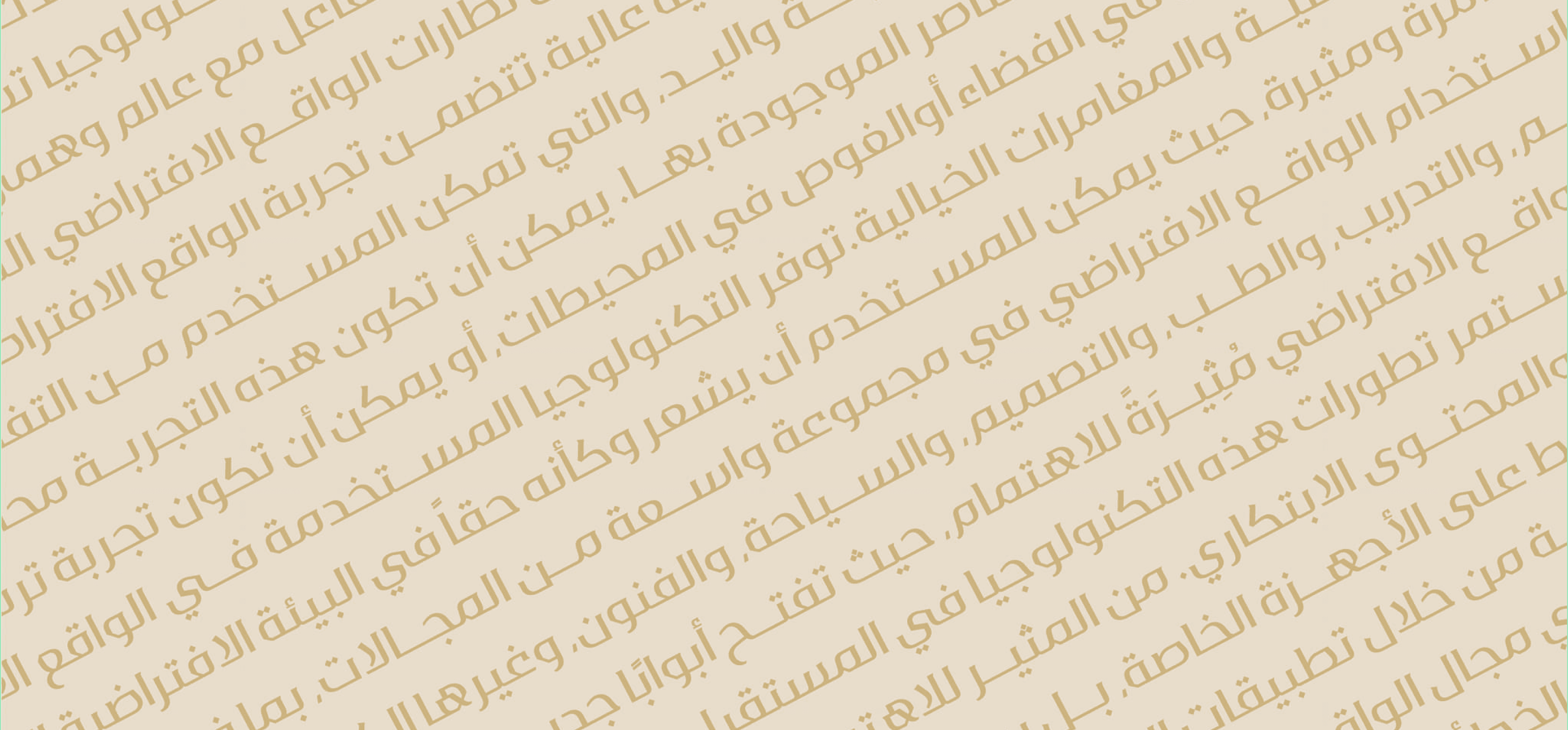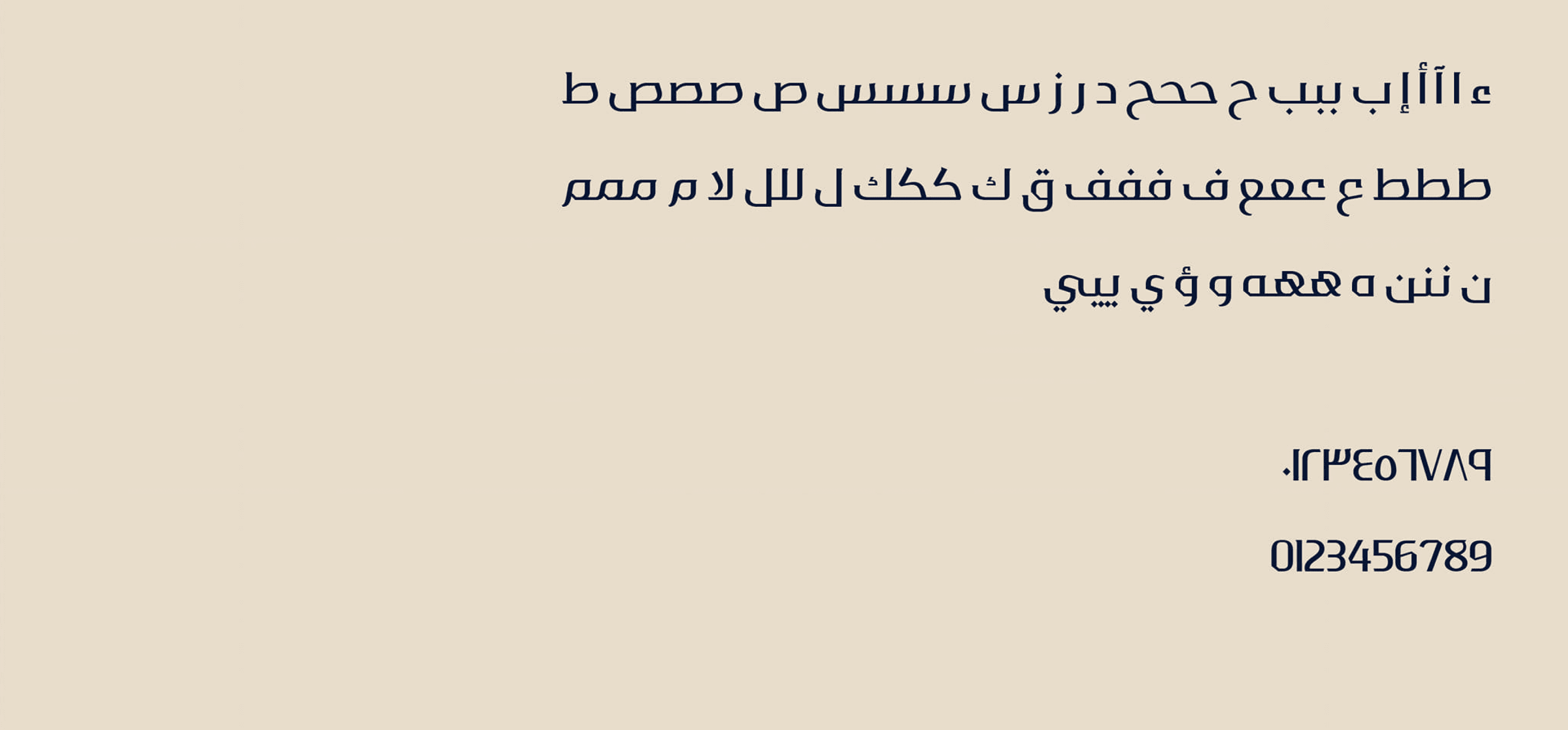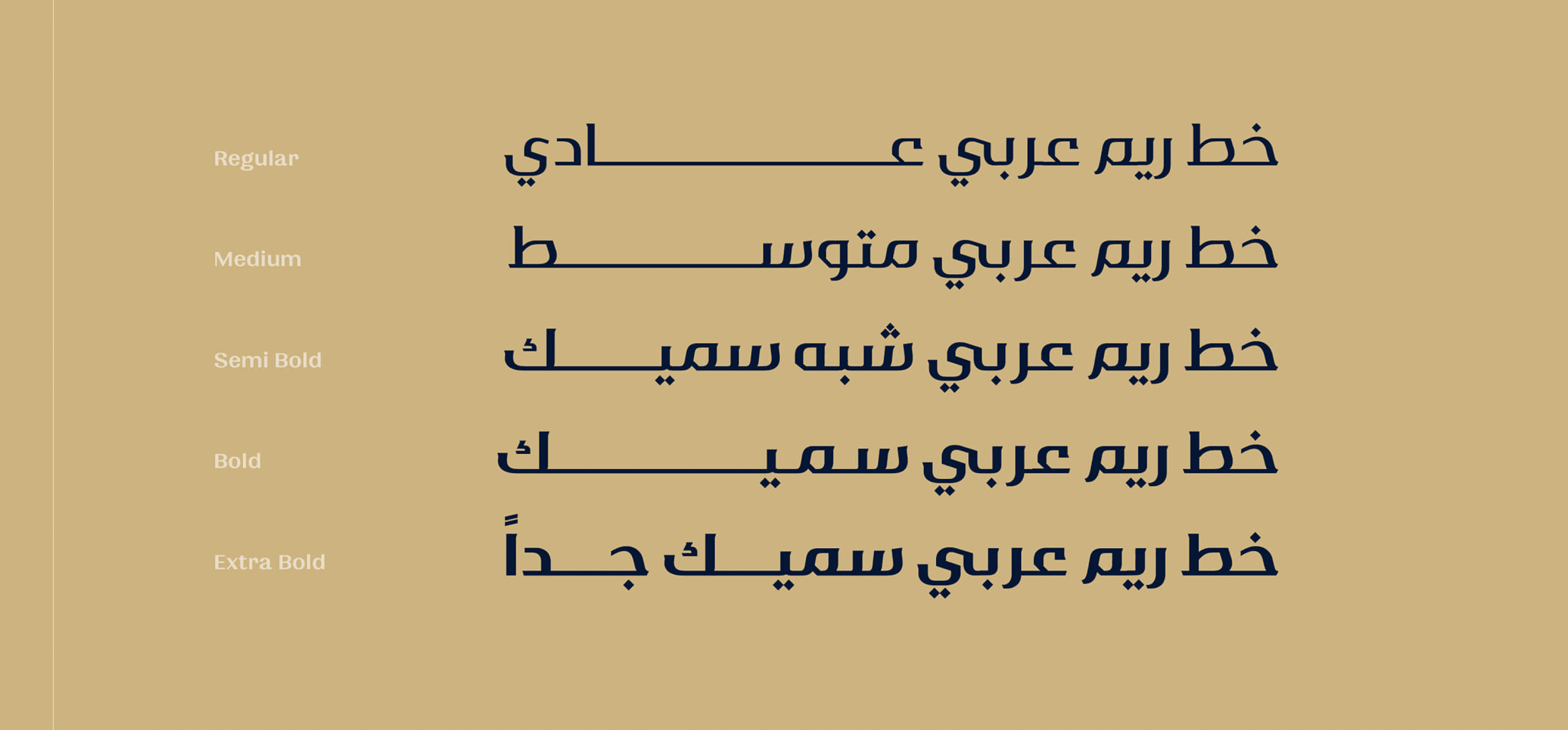
إليكم خطاً عربياً جديداً كلياً، تم تصميمه بعناية فائقة بيديك، مستلهماً من عمق الثقافة العربية وتراثها الغني. يجسد هذا الخط رؤيتك الإبداعية وتعبيرك الفني الخاص، حيث يدمج بين التقنيات الحديثة والفهم العميق لجماليات اللغة العربية.
تم تطوير هذا الخط باستخدام أحدث الأساليب لضمان وضوح ممتاز وسهولة قراءة عالية. فقد تم دراسة كل شكل وخط وتفصيل بعناية للوصول إلى توازن مثالي بين الأناقة والوضوح.